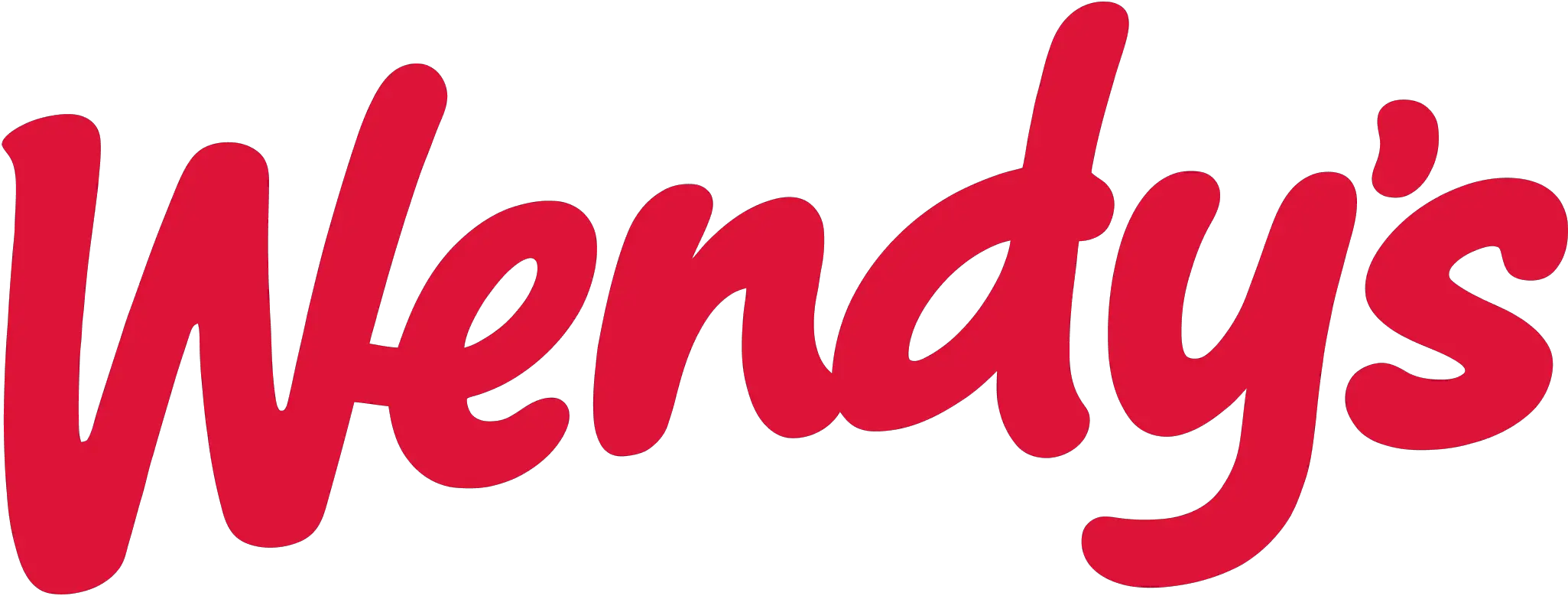
Fuente del logotipo de Wendys (antigua y nueva)
Publicado: 2023-03-29Para que este artículo se considere útil, me gustaría describir brevemente a Wendys y su creciente popularidad, la importancia de la marca y la identidad visual para una empresa, y el propósito del artículo, que es hablar sobre la fuente Wendys y cómo descargarla. él.
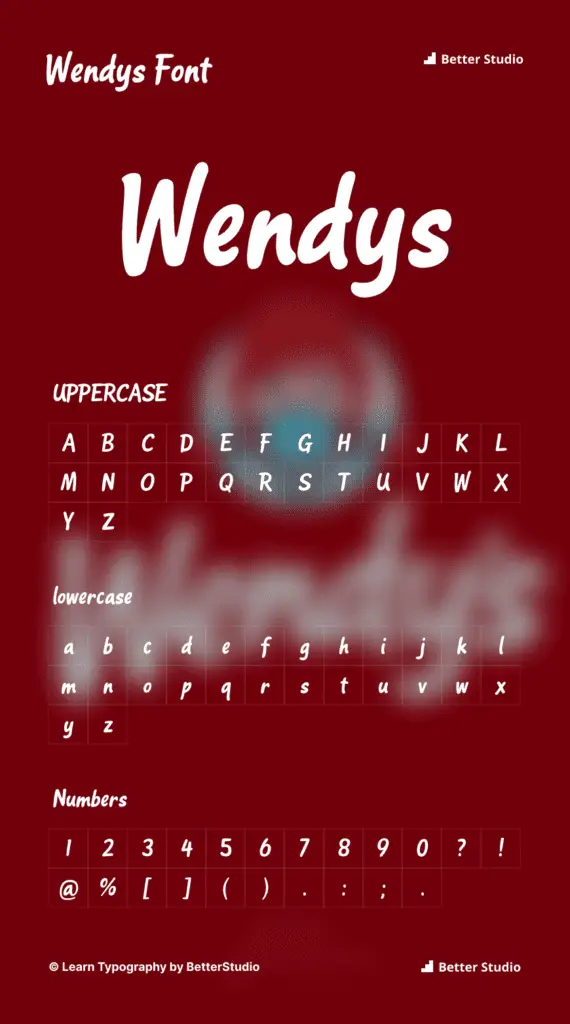
¿Qué fuente utiliza el logotipo de Wendys?
Al diseñar el logotipo de Wendy's, se siguió un conjunto específico de especificaciones, pero es difícil determinar un tipo de letra específico que se utilizó para crear el logotipo.
A pesar de esto, las fuentes Wendy's Script y Wendyville son sorprendentemente similares a la fuente del logotipo de Wendy's que se traslada a Wendy's Script.
Puede usar esta fuente para crear proyectos con un aspecto similar al logotipo de Wendys y también acceder a los caracteres alfabéticos y numéricos que pueden ser útiles para su proyecto si es necesario.
También debe notar que el archivo incluido para descargar la fuente Wendys consta de dos tipos diferentes de fuentes: el antiguo y el nuevo tipo de fuente Wendys.
Alternativas y estilos de fuente similares a Wendy's Script y Wendyville
Las siguientes son 5 fuentes que son idénticas en diseño y similares en uso a Wendy's Script y Wendyville si está buscando una alternativa o un estilo similar a esas dos fuentes:
- Fuente Amsterdamsk
- Fuente de la pesadilla de Burton
- Fuente Nightwish
- Fuente de ensueño de Sicilia
- Fuente de escritura a mano de Wendy
¿Cuál es la mejor manera de usar la fuente Wendys?
¿Quién diseñó la fuente Wendys?
El diseñador de la fuente Wendy's Script y Wendyville aún se desconoce en este momento, pero se especula que ambas fueron diseñadas por un diseñador tipográfico estadounidense llamado Gert Wagner a fines de la década de 1950.
Conocido por muchas fuentes que diseñó, incluidas ITC Souvenir, Handel Gothic y Times Roman, Wagner fue un destacado diseñador tipográfico.
Una descripción general de Wendys
Es uno de los restaurantes de comida rápida más conocidos de Estados Unidos principalmente por sus combos de sándwiches, ensaladas y Frosties. La cadena de restaurantes Wendy's fue fundada en 1969.
A lo largo de la garantía de marca de Wendy's, las fuentes Wendy's Script y Wendyville se han utilizado a lo largo de los años, pero su logotipo icónico no ha cambiado desde 1969.
Hay muchos detalles distintivos sobre este guión que se han vuelto reconocibles como parte de la marca Wendy's y, a menudo, se los denomina "la tipografía de Wendy's".
Una variedad de otros elementos constituyen la identidad corporativa de Wendy's, como la clásica paleta de colores rojo, blanco y negro, el uso de su mascota y la señalización icónica de la compañía y una variedad de otros elementos.
Al combinar todos estos elementos, Wendy's ha creado una apariencia uniforme que se reconoce al instante y se ha convertido en sinónimo de la marca Wendy's en su conjunto.